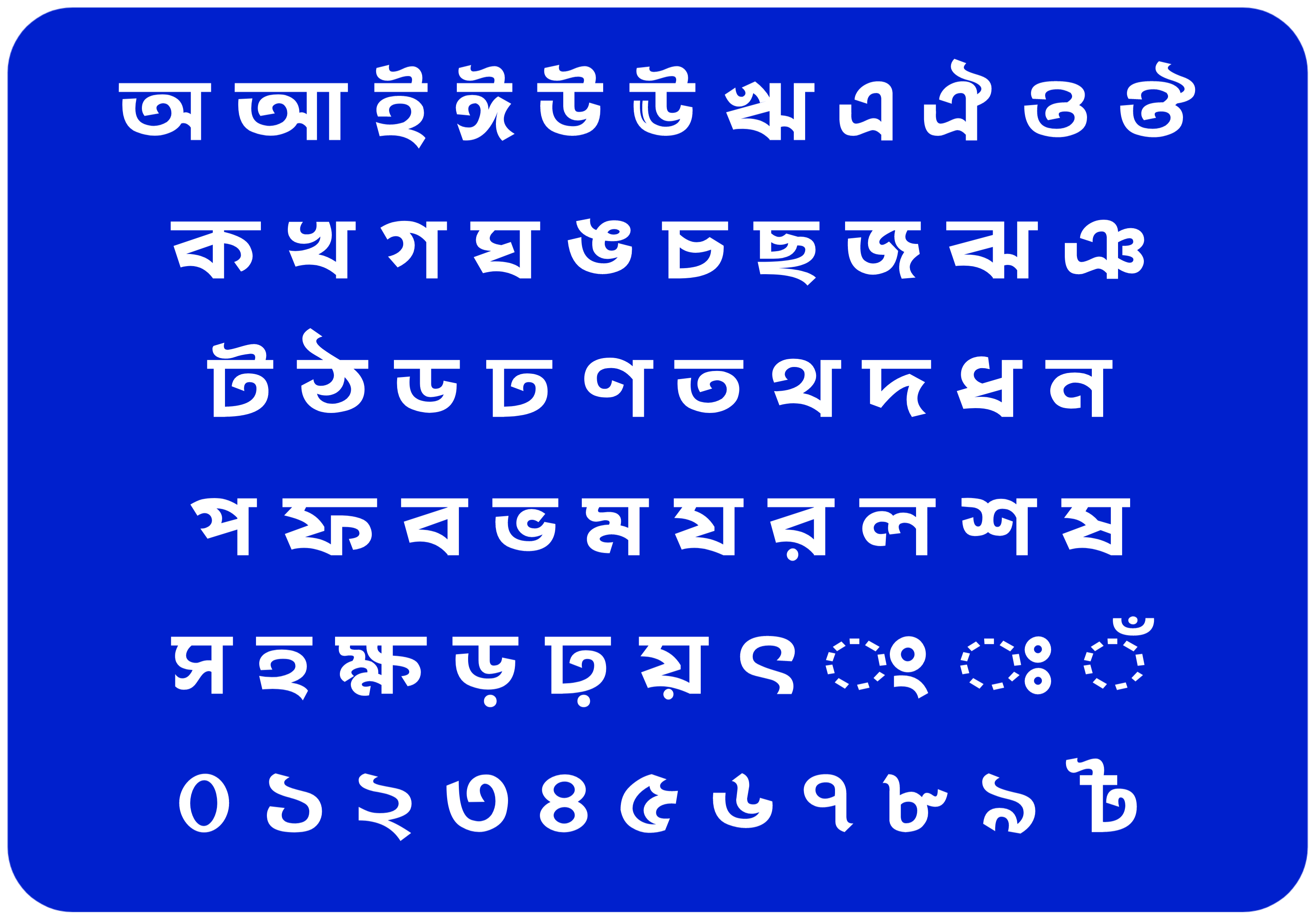
বিটপি হলো বাংলা ফন্ট জগতে সবচেয়ে বহুল ব্যবহৃত এবং প্রচলিত ফন্টগুলোর মধ্যে অন্যতম। এটি একটি মিনিমাল প্যারাগ্রাফ ফন্ট যা যেকোনো কাজে সহজেই ব্যবহারযোগ্য, মানানসই এবং বোধগম্য। ব্যক্তিগত বা ছোটখাটো কাজের পাশাপাশি বড় বড় কমার্শিয়াল কাজেও ফন্টটি বেশ জনপ্রিয়। ফন্টটির নির্মাতা জনপ্রিয় বাংলা ফন্ট ডিজাইনার এবং ডেভেলপার জনাব সাইদ আলমগীর।
বিটপি
- নকশাকার : সাইদ আলমগীর
- বিকাশকারী : সাঈদ আলমগীর
- রূপ : ১ টি
- বর্ণের ভাষা : বাংলা